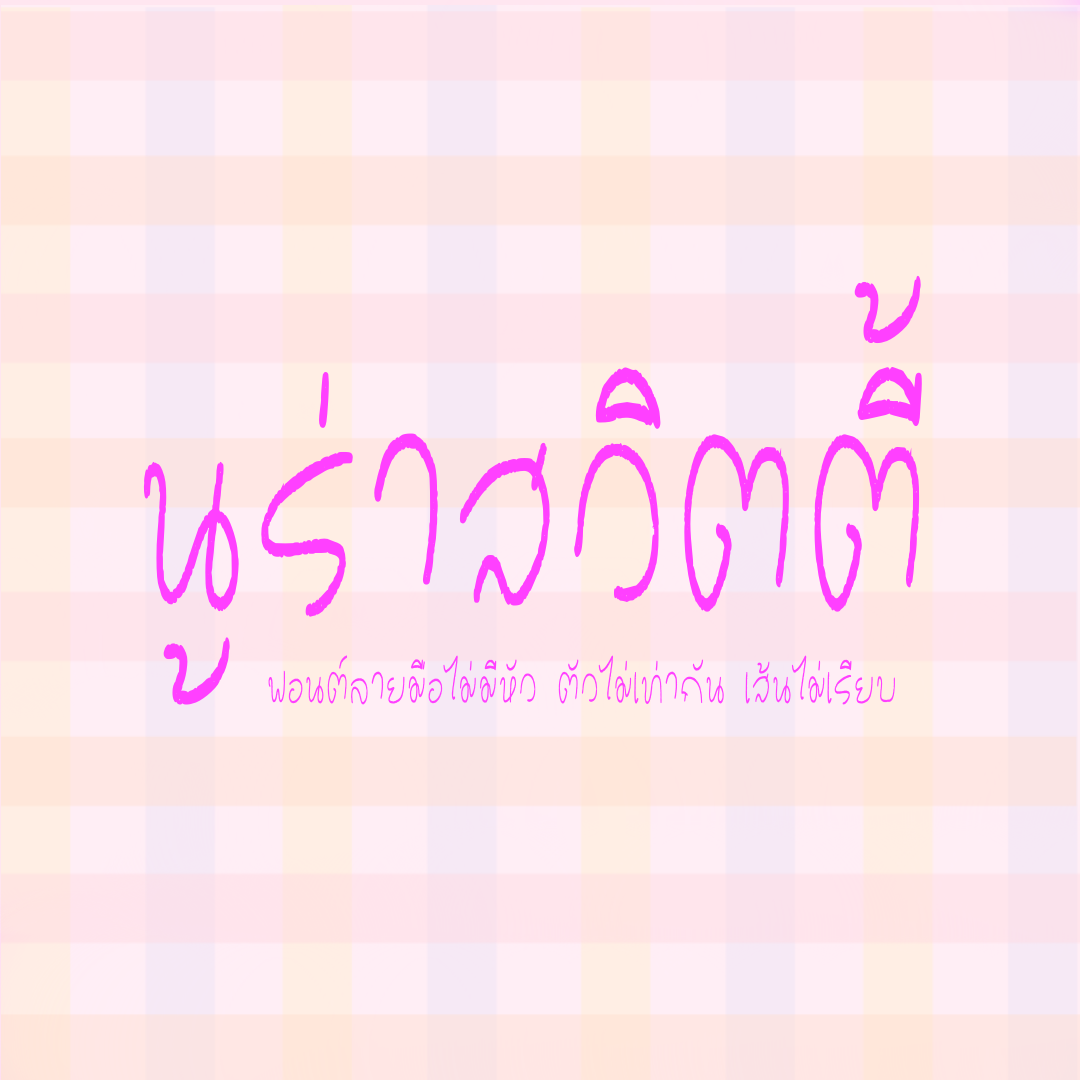
นูร่าสวิตตี้ (Nura sweety)
ฟอนต์ลายมือตัวบางๆ ผอมๆ ไม่มีหัว  เส้นหยัก ตัวไม่เท่ากัน มีด้วยกัน 6 น้ำหนัก คือ บาง ปกติ หนา บางเอียง ปกติเอียง หนาเอียง นูร่าราดาเปิดให้ใช้ฟรีส่วนตัวน้ำหนักบาง และหนาเอียง นะคะ